Apple впервые за 16 лет поменяла шрифт на клавиатуре MacBook
Шрифт на клавишах новых ноутбуков Apple, представленных на конференции Spring Forward в понедельник, изменился впервые за 16 лет. Об этом сообщает Look At Me со ссылкой на The Next Web.
Apple использовала на клавиатурах один и тот же шрифт с момента запуска линейки iBook в 1999 году. Всё это время на MacBook был шрифт VAG Rounded, который в 1978 году разработали для Volkswagen. На клавиатурах нового макбука используется San Francisco Display – основной шрифт интерфейса Apple Watch. Вероятно, стоит ожидать, что в будущем Apple заменит VAG Rounded и на других своих продуктах. Шрифт San Francisco ранее присутствовал только в спецификации Watch OS.
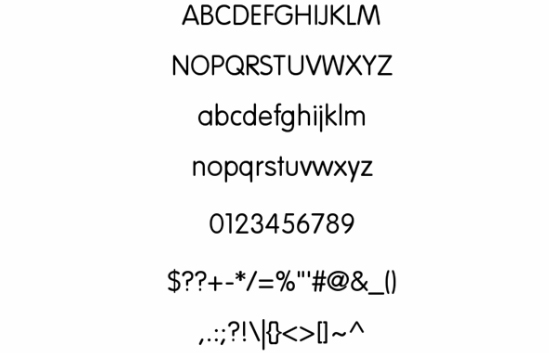
VAG Rounded
VAG Rounded — шрифт без засечек, который разработали для объединённой дилерской компании Volkswagen и Audi. До этого в Volkswagen использовали Futura, а в Audi — Times. Компания прекратила его использовать в 1992 году. Позже шрифт появлялся в документации компании T-Mobile, логотипе Big W, а также рекламах Woolworths, Bankwest, Adecco и других.
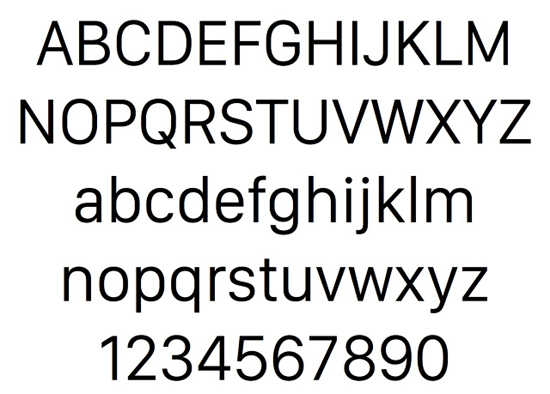
San Francisco Display